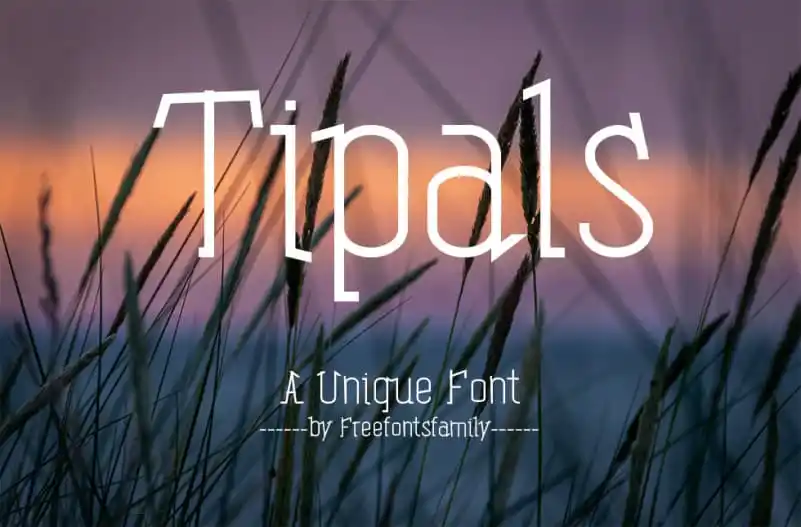
Tipals Font – Fonte Grátis
Tipals Font
Introduzimos a fonte Tiplas projetada para atender às necessidades de todos os designers. Esta elegante font é perfeita para criar designs históricos, citações ou capas de livros. Com ela, você pode tornar suas criações ainda mais atraentes e únicas. Além disso, esta font é ideal para branding, elevando seu projeto gráfico a um novo patamar. Estamos ansiosos para que você descubra como Tiplas poderá revolucionar seus projetos visuais. Ideal tanto para designers de sites quanto para aqueles especializados em editoração e design gráfico, essa font permite uma expressão única e personalizada. Com a capacidade de adaptar a Tiplas à sua necessidade específica de criação visual, você terá o poder de fazer suas mensagens mais impactantes e memoráveis. Experimente agora e veja como essa font pode transformar seu trabalho em design!